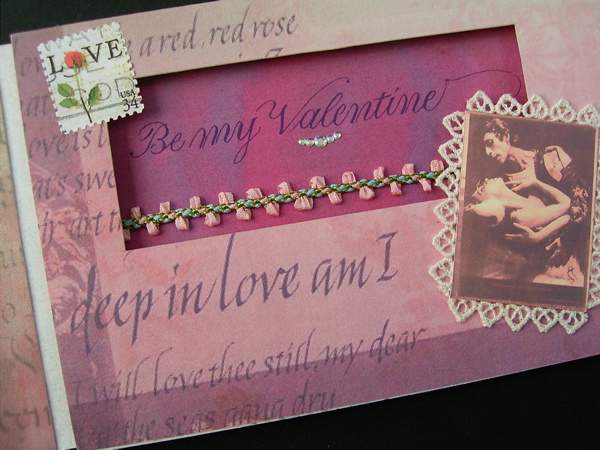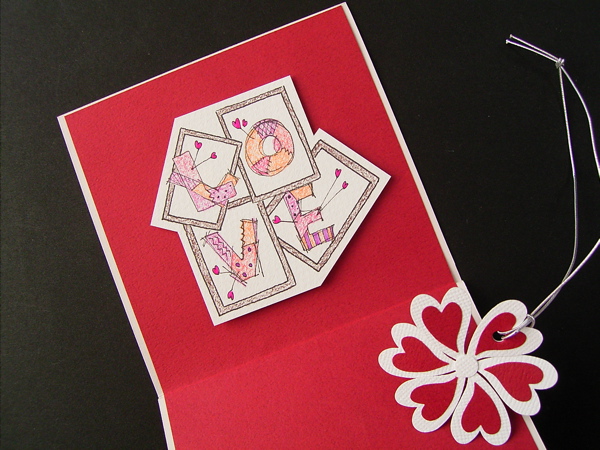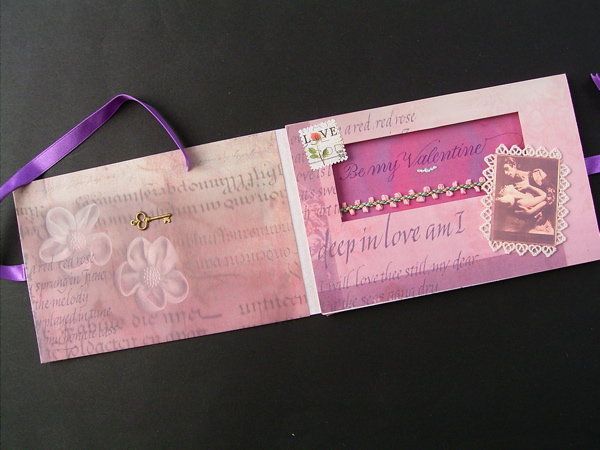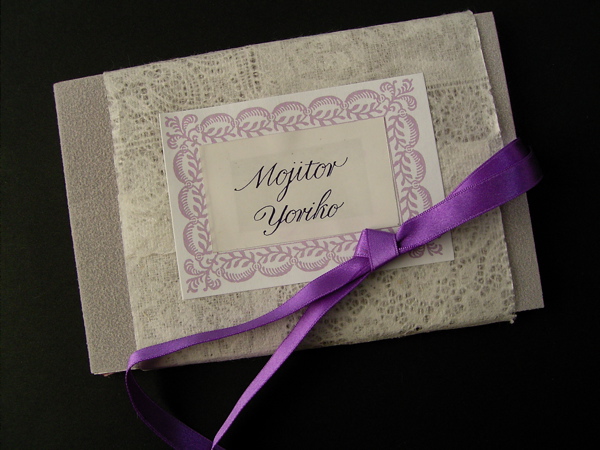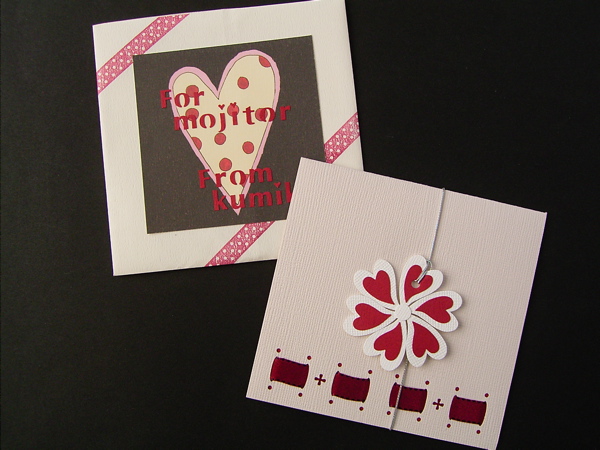
2月のエクスチェンジカード
あっという間にバレンタインデーが過ぎ、買ったりもらったりしたチョコレートもなくなりつつ(体重は増えつつ)ある今日このごろ。
今月のエクスチェンジカードをご紹介します!
2月はバレンタインデーがあるので、うふふ、愛のカードが届きましたよ〜。
こちらはKIさんの作品です。クラフトパンチのアルファベット、初めて見ました!こんな感じなんですね。ひとつひとつをパンチして置いていくのが難しそうですが、きっとkumikoさんならピンセットでヒョイヒョイと貼っていかれるのでしょうね。このハートの方は、封筒なのです。中身はこちら。
開けるとポップなLOVEの文字が立体的に出てきます。とにかくクラフトパンチを上手に使ってあってとても参考になるカードです。このお花もハートを組み合わせて出来ているんです。
紙の種類もいろいろと吟味して選んでいらっしゃって、売り物のように完璧です。すごーい!またパンチが欲しくなってしまいます。
さてもう一点は、これまた手が込んでいるカード。YEさんの作品です。さてさて、一体どうやって作られたのでしょう!!
しかも、文字はいくつも重ねてあって、奥行きがあります。これは一体どうやって作られたのでしょう〜!
中に貼ってある右下のバレリーナのカップルの写真は、なにやらロマンス〜という感じです。ひょ〜・・!
左側には鍵が付いているし、うーむ、何か意味があるのですね。
こんなカードを殿方がもらったら、イチコロですね。きゃー!
このクラフトパンチは、ミニミニサイズなので、
のりがはみ出さないように、のりはほんのちょっと、
そぉ〜っと、そぉ〜と封筒に貼りました。
慎重にしていても、置こうと思ったところからずれてしまったり
「ひぇ〜!」失敗ということもあります。
YEさんのカード、大人っぽく、とても素敵ですね〜。
パンチの使い方 ス・テ・キです。まねしちゃいます。